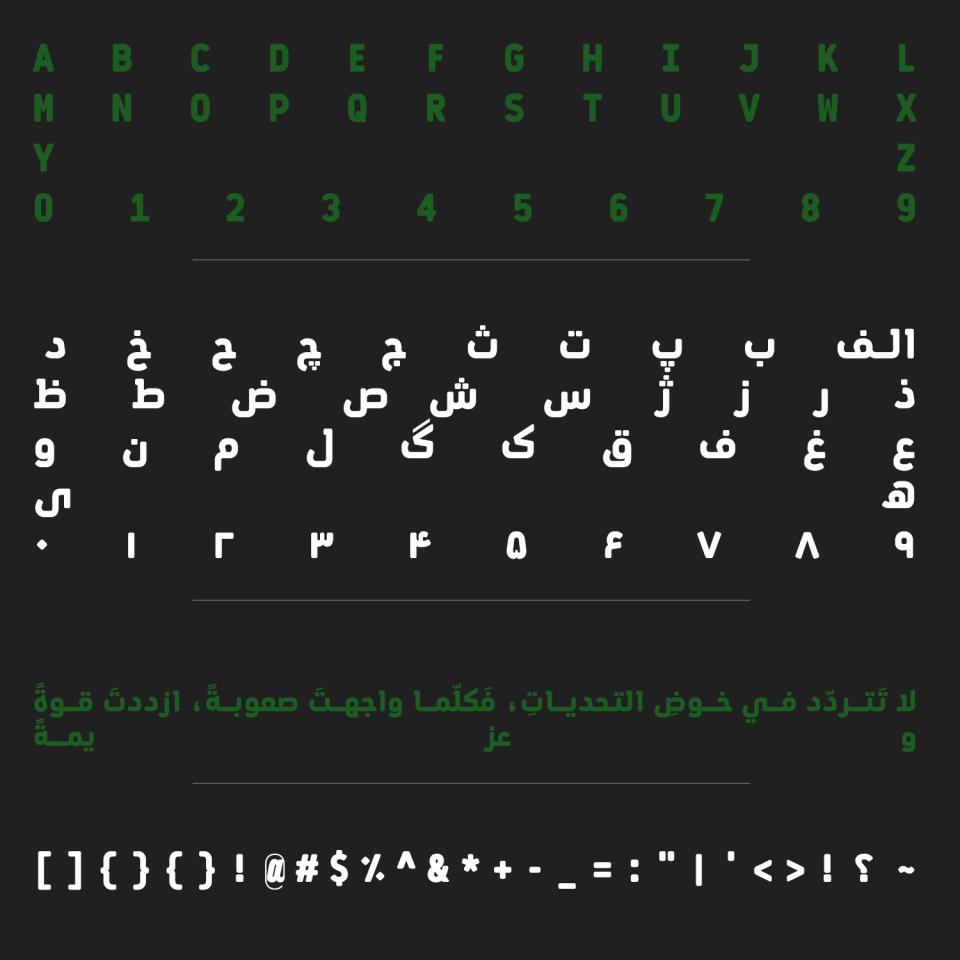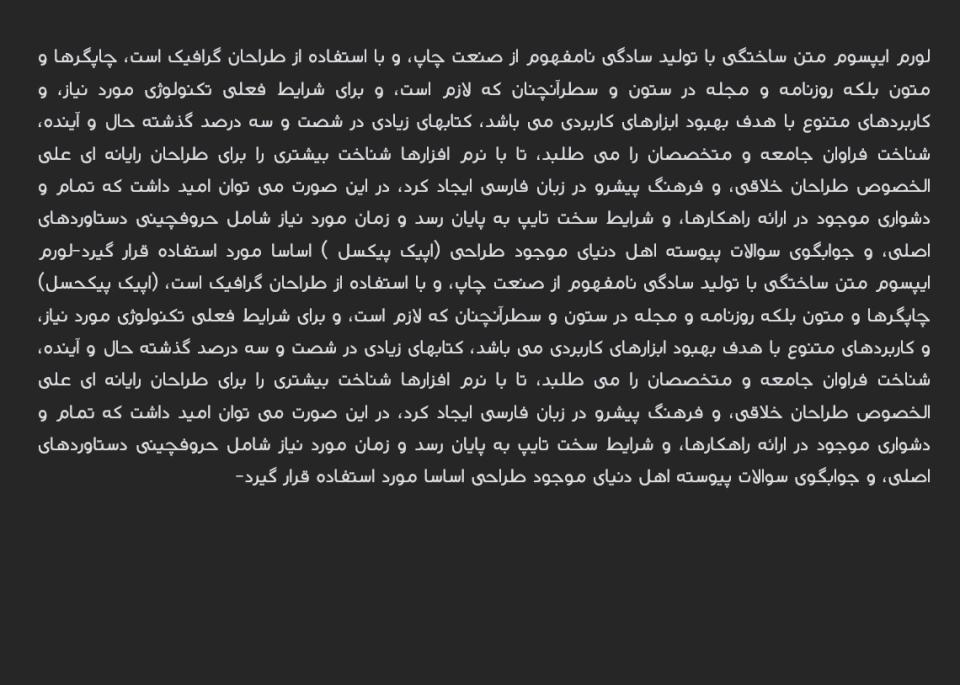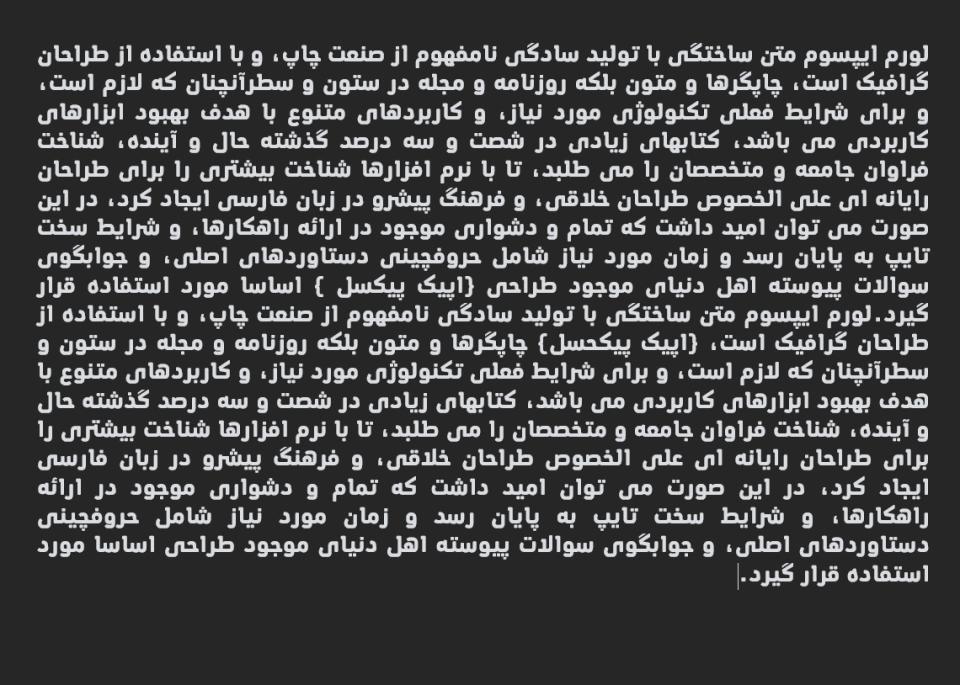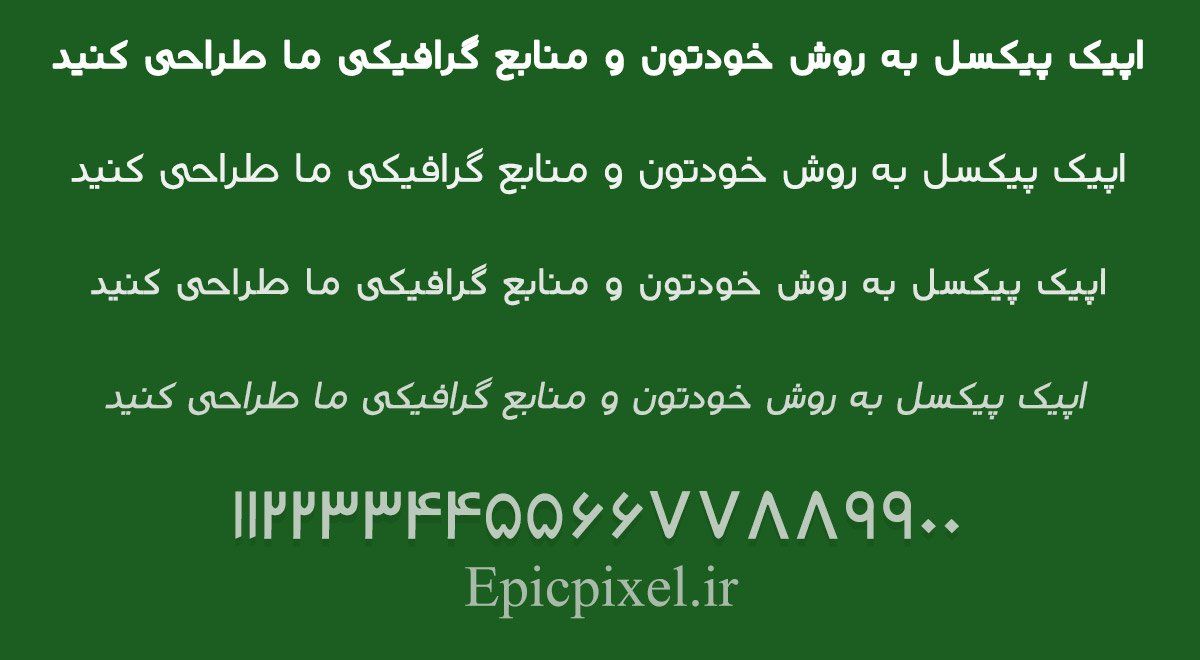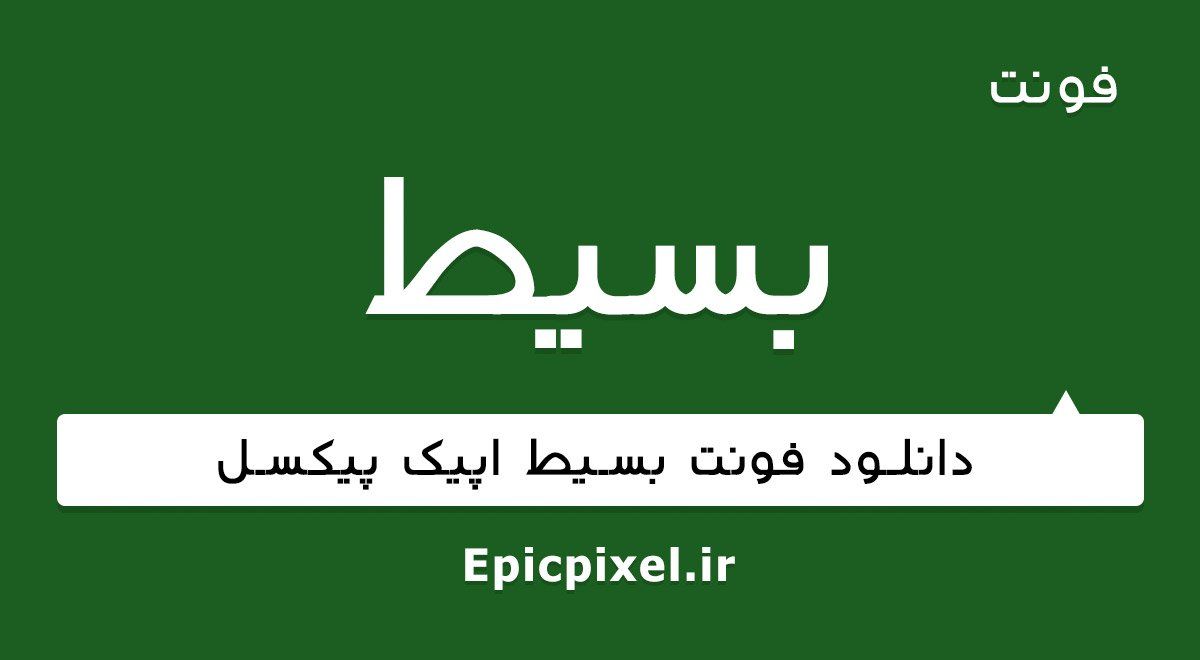
5 فونت بسیط فارسی
فونت بسیط فارسی، با طراحی منحصر به فرد خود، تجربه ای نوین از خوانایی و زیبایی را به ارمغان می آورد. این فونت با ساختار ساده و در عین حال چشم نواز خود، در انواع طراحی ها، از وب سایت ها و اپلیکیشن ها گرفته تا کتاب ها و مجلات، جلوه ای خاص ایجاد می کند.
یکی از ویژگی های برجسته فونت بسیط، هماهنگی بی نظیر حروف آن با یکدیگر است که خواندن متن را بسیار آسان و روان می سازد. این ویژگی به ویژه در متون طولانی، از خستگی چشم جلوگیری کرده و تجربه کاربری بهتری را فراهم می کند. علاوه بر این، طراحی این فونت به گونه ای است که در اندازه های مختلف، چه کوچک و چه بزرگ، وضوح و خوانایی خود را حفظ می کند.
فونت بسیط فارسی، با ارائه ترکیبی متعادل از سادگی و زیبایی، به طراحان کمک می کند تا آثاری خلق کنند که هم جذاب و مدرن باشند و هم خوانا و کاربرپسند. اگر به دنبال فونتی هستید که به طراحی های شما هویتی متمایز ببخشد و در عین حال تجربه کاربری مطلوبی را فراهم آورد، فونت بسیط فارسی انتخابی ایده آل برای شماست. این فونت رایگان است و به راحتی می توانید آن را دانلود و در پروژه های خود استفاده کنید.